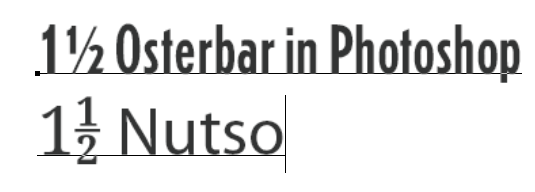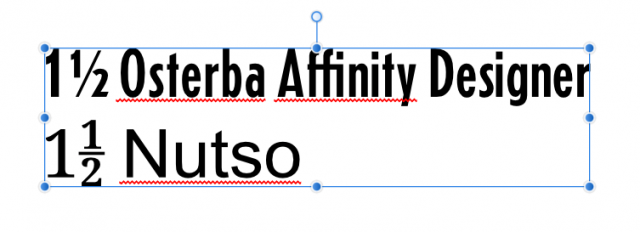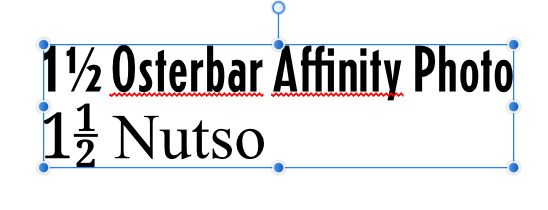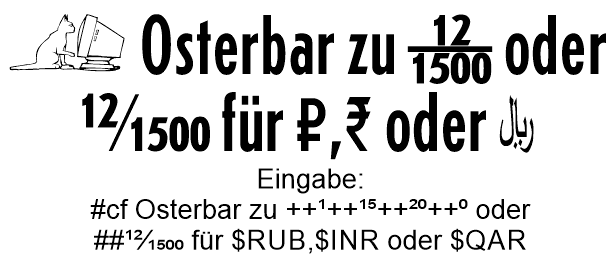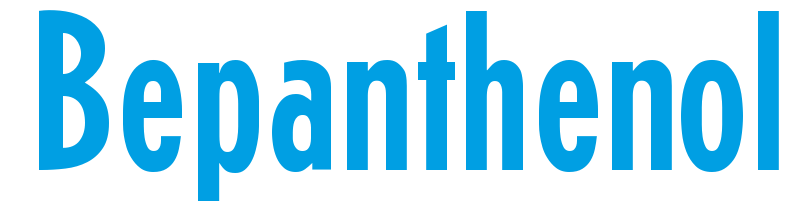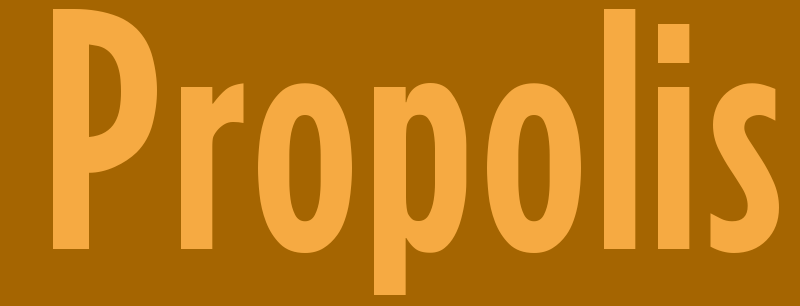
Schrift von DDR-Warn- und Hinweisschilder
Wunderbar!
Dann braucht die wohl ...
Und schön, dass die Ligaturen auch ohne Opentype funktionieren:
Nö, aber Deine Software kann wenigstens das OT-Feature liga.
@catfonts Hallo Peter, ich habe eine Schrift gefunden, die Brüche so darstellt dass sie in Indesign auch funktionieren. du kannst ja in openoffice mal probieren ob das auch bei dir funktioniert.
https://github.com/TiroTypeworks/Nutso
in den Test pdf´s kann man das Ergebnis sehen. muss nur mal studieren wie man die dann schreiben muss, damit die auch so aussehen.
Ergebnis folgt.
@catfonts  im Ordner third party sind auch noch schriften drin, möglich dass da bessere Ergebnisse kommen.
Edit: leider nicht, da ändert sich nix
Und hier ist eine schnell gestrickte Live-Testseite für die Opentypefunktionen: http://type.dt1.org/font/cat/osterbar/
:tuschel: $euro wäre vielleicht noch ein praktischer Code für Leute ohne €-Tastatur.
jepp oder eben $EUR um bei der Iso zu bleiben. also 3 Buchstaben
das hier ist genau das was wir brauchen. allerdings sieht das noch in indesign und illustrator nicht so aus.
Ich habe gerade die ganzen Währungscodes umgebaut (noch nicht im Download)
Hier habe ich dann (nahezu?) alle ISO 4217 Currency Codes mit den 3 Buchstaben umgesetzt, und als Steuerzeichen wahlweise $, € und das allgemeine Währungszeichen eingesetzt. So ergibt natürlich auch ein $USD auch wieder $, aber ebenso ein €USD oder ein ¤USD. Währungscodes, die dann aus einem oder mehreren Buchstaben bestehen sind dann durch entsprechende Ligaturen wiedergegeben, die zum Text etwas kleiner sind.
Dass Word 2013 das Thema OpenType recht eigenwillig sieht, und nur einige Teilbereiche unterstützt, ist nun mal leider so. Aber offensichtlich hakt es auch bei Illustrator noch.
jepp leider Peter, aber das ist HEUTE (Mittwoch) nicht mehr dein Problem. Schade da ich [Ai] lieber benutze als [Id]. aber man kann ja nicht alles haben :-) werde morgen (ach nee heute) mal weitersuchen, denn das problem haben viele, die brüche eben so darstzellen müssen wie es hier gebraucht wird. waagerecht.
Ich bin schon zufrieden, wenn es in einem der beiden Programme funktioniert. wenn widererwartent doch noch eine Lösung für [Ai] kommt um so besser. Word ist sowieso nicht wirklich mein Freund. Benutze ich eher widerwillig.
in [Id] gibts ja die Option in Pfade zu wandeln, da es in einer importierten PDF in [Ai] ähnlich schlecht ausschaut.
Und LibreOffice ist da eben phantastisch. Hier funktionieren sogar OpenType-Layout-Tags, wenn ich deren Namen selbst erfinde. Die Hauptsache die Ersetzungsregeln darin entsprechen der richtigen Syntax
also in [Ps] funktioniert deine Schrift wieder nicht.
Hier kann man gut sehen, dass in den unterschiedlichen Programmen immer noch kein Gleichstand vorherrscht. Das kommt davon wenn unterschiedliche Programme gekauft werden und unter einem Dach vereint werden.
Ich werde noch Affinity probieren. Wenn du in Corel mal eine Zeile setzen könntest hätten wir schon ein anderes Produkt. Man könnte ja auch am Ende eine Zusammenfassung machen.